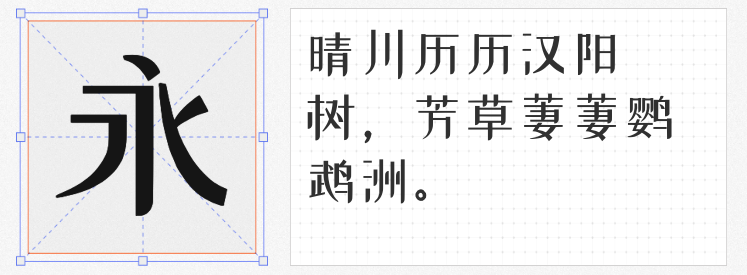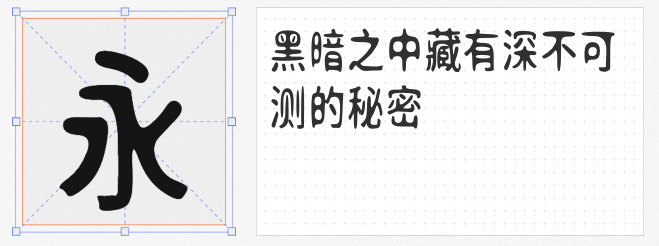
在LOGO设计中,字体的选择直接影响品牌调性的传达。本文精选四款免费商用且风格独特的字体,涵盖现代几何、动态科技、趣味实验与文化创意四大方向,为设计师提供高辨识度解决方案。
由设计师李大卫团队打造的站酷小薇LOGO体,以剑形笔画为灵感,6763个汉字通过几何化处理实现视觉突破。其撇捺末端采用切断式设计,捺画以直角收尾,配合转折处的硬朗倒角,形成如兵器般的锐利感。尽管简化部分笔画,但通过中宫扩张与重心上移设计,确保小字号下的识别度。该字体已应用于科技、文创等领域LOGO,尤其适合追求未来感与力量感的品牌。
作为斗鱼品牌升级的核心字体,斗鱼追光体2.0以向右8°倾斜构建速度意象,横细竖粗的笔画对比强化视觉张力。设计师创新性地将LOGO中鲨鱼鳍弧度转化为笔画倒角,包围结构采用切口处理提升透气性。6763个字符支持全场景应用,从直播平台到硬件产品,其科技感与娱乐性平衡的设计语言,成为互联网企业LOGO设计的热门选择。
基于思源黑体改造的新愚公迷茫体,通过随机扭曲算法赋予文字融化般的动态效果。每个字符的笔画粗细、弧度均产生微妙差异,形成类似古印章的残缺美感。这种不确定性设计虽挑战传统识别逻辑,却为艺术展览、独立品牌等场景提供强烈视觉符号。需注意在正文中需搭配标准字体使用,避免影响信息传达。
仓耳字库将金石篆刻的刀痕转化为字体骨骼。其特色在于“口”部结构的圆角处理与竖画的刀刻质感对比,形成外刚内柔的视觉层次。配套英文采用相同设计语言,解决中英混排时的风格割裂问题。该字体在文化机构、传统工艺品牌的LOGO设计中表现突出,传递出厚重而不失现代感的气质。